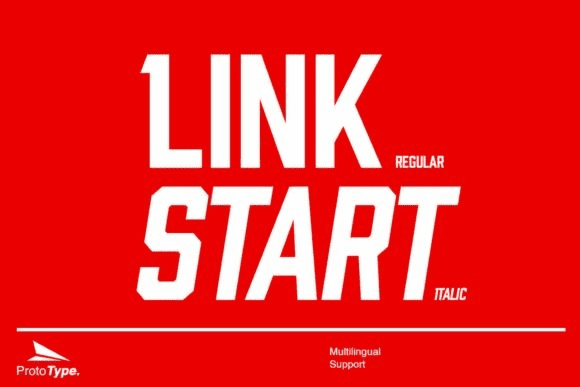
Link Start
- это крутой, толстый и современный шрифт с наклонной засечкой.
Используйте его в любом дизайне, связанном со скоростью, силой или спортом, и вы будете поражены конечным результатом.